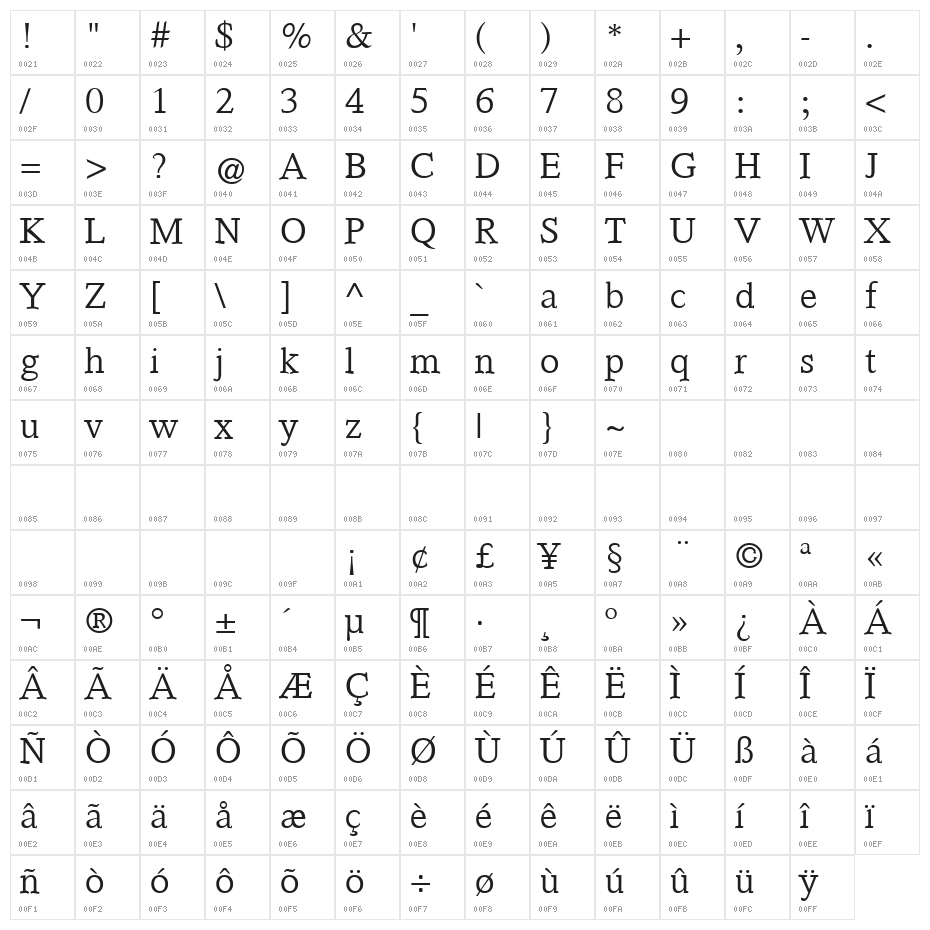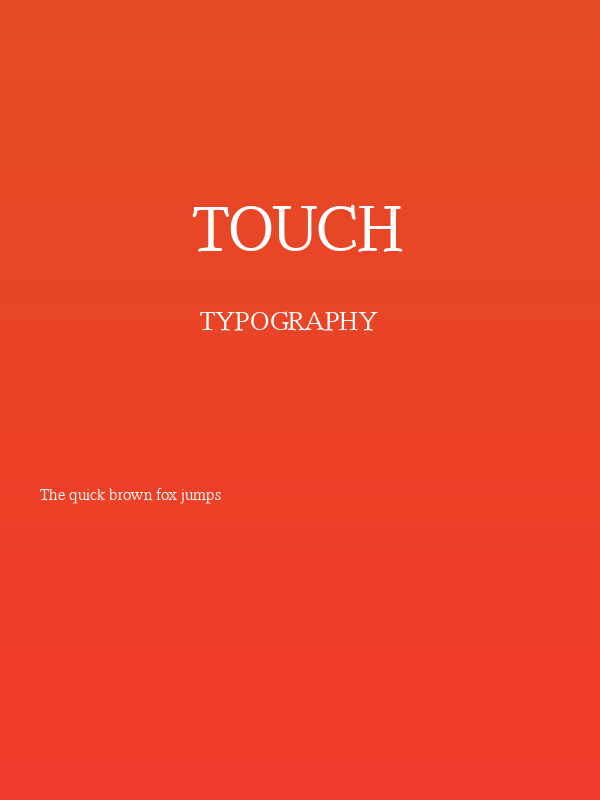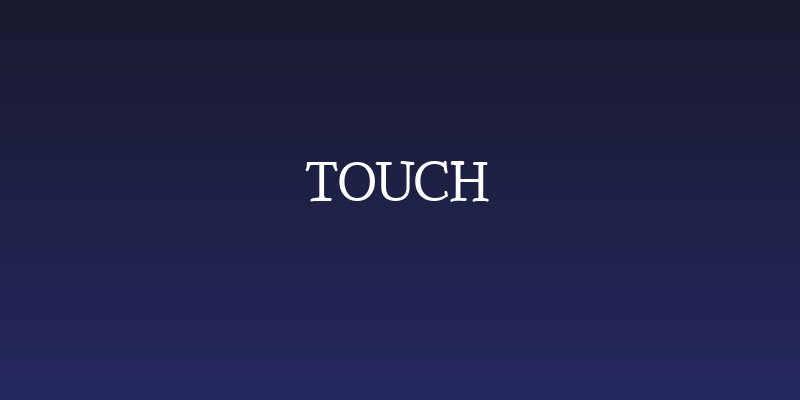
Touch Font
| Kategorien | Serif |
| Gesamtstil | Classic |
| Anwendungsfall | Headlines, Body text, Logos |
| Vorgeschlagene Projekte | This font is perfect for editorial design, book covers, formal invitations, branding for luxury products, and any project requiring a touch of elegance and tradition. |